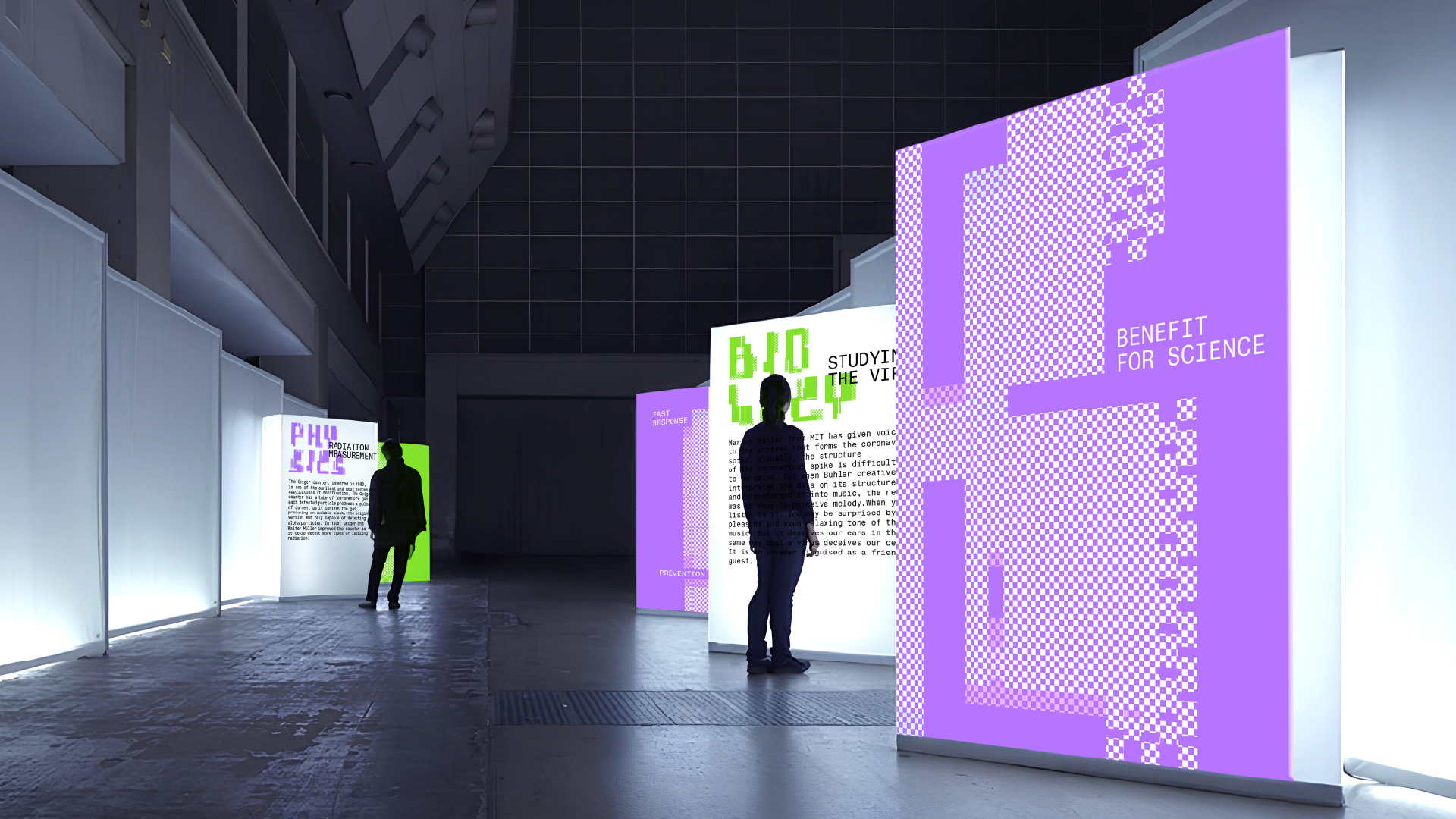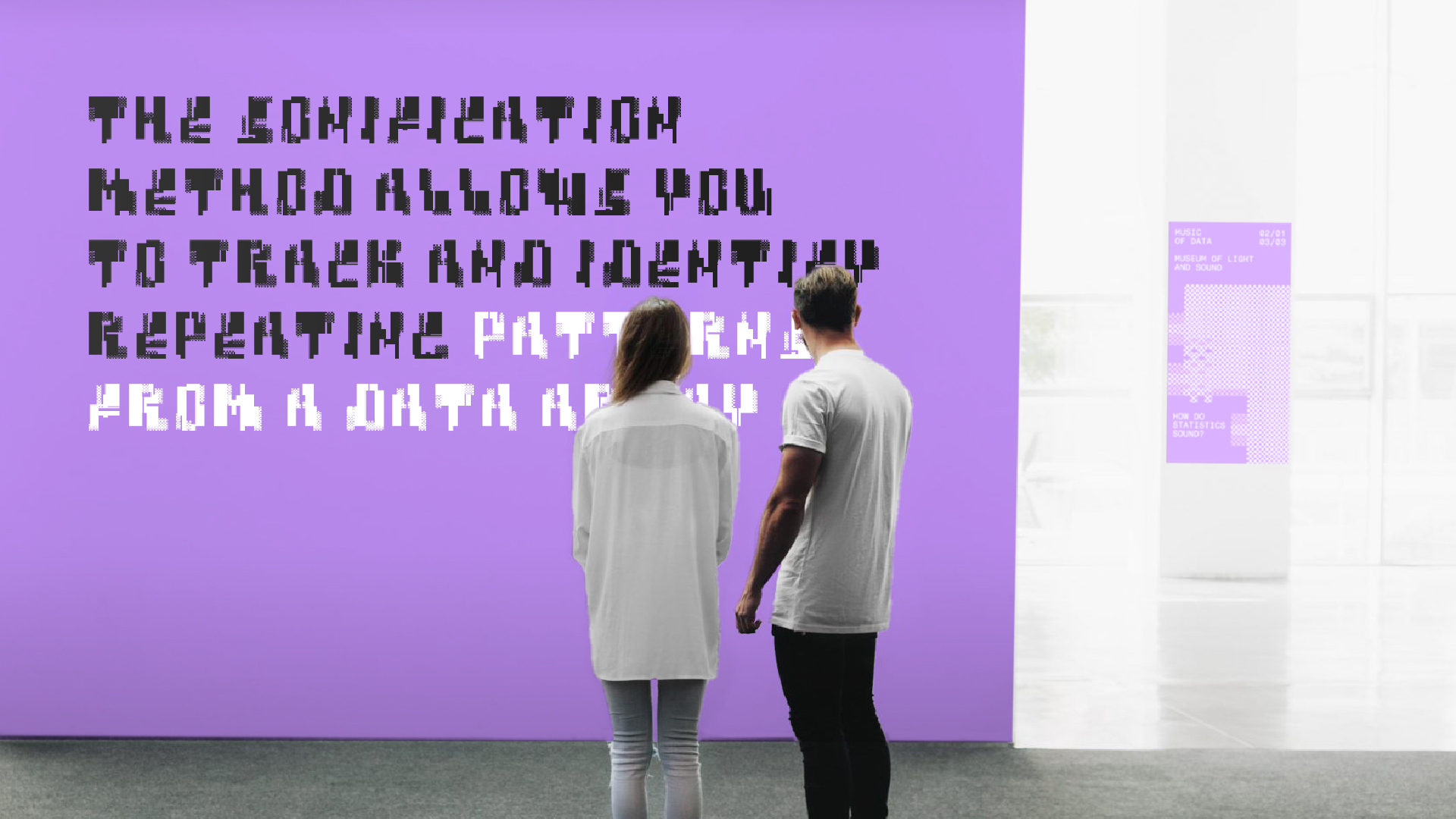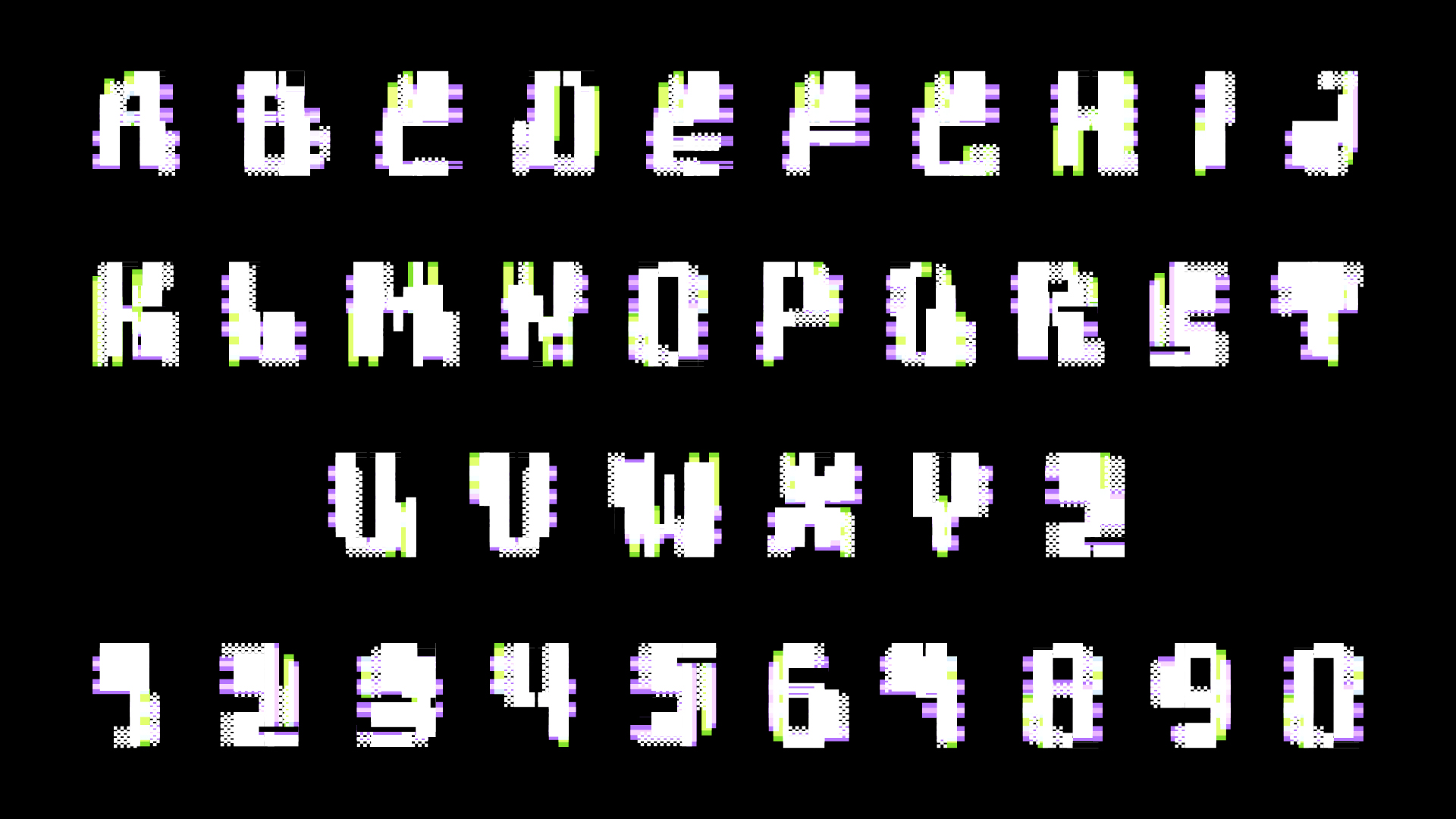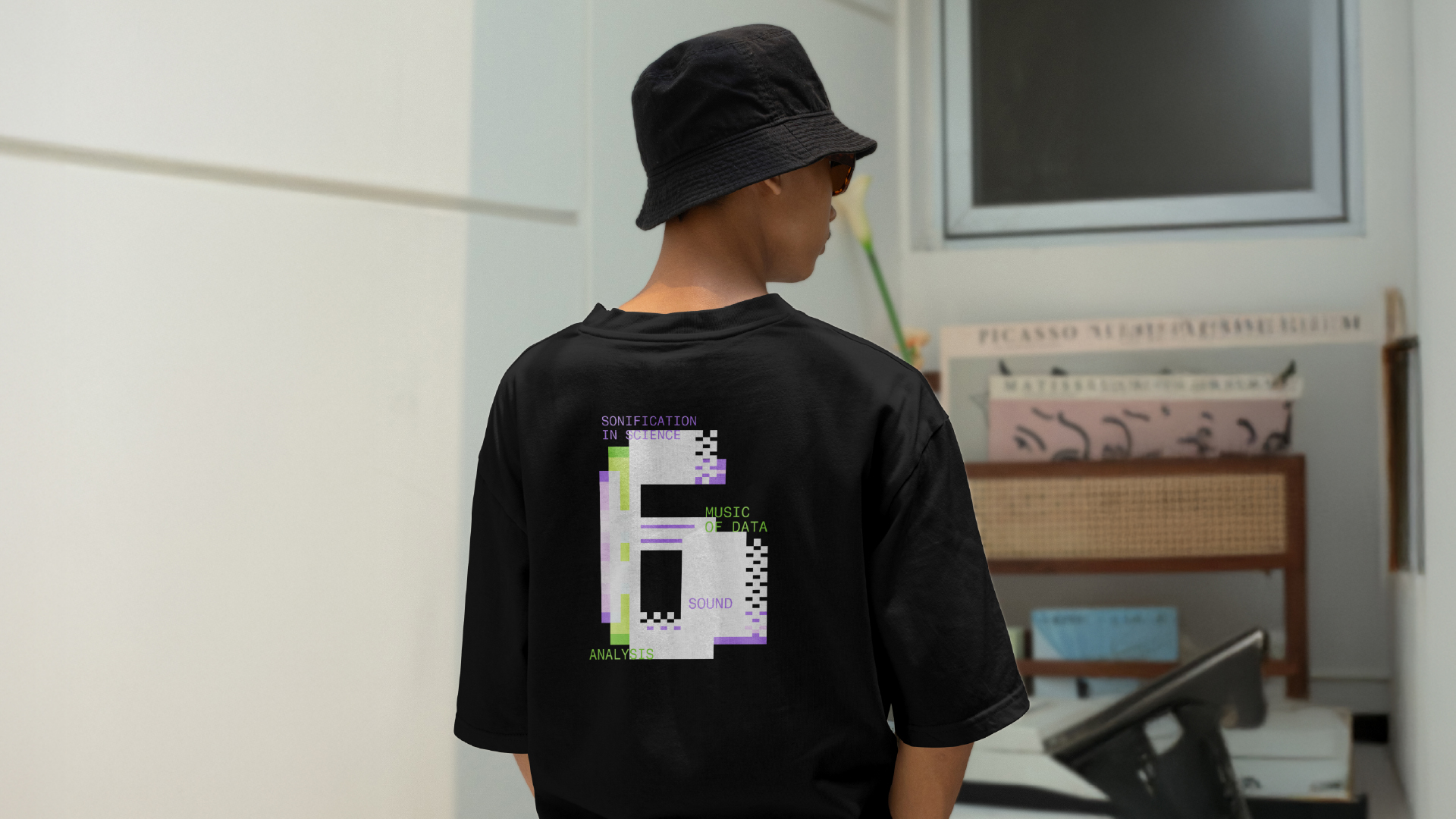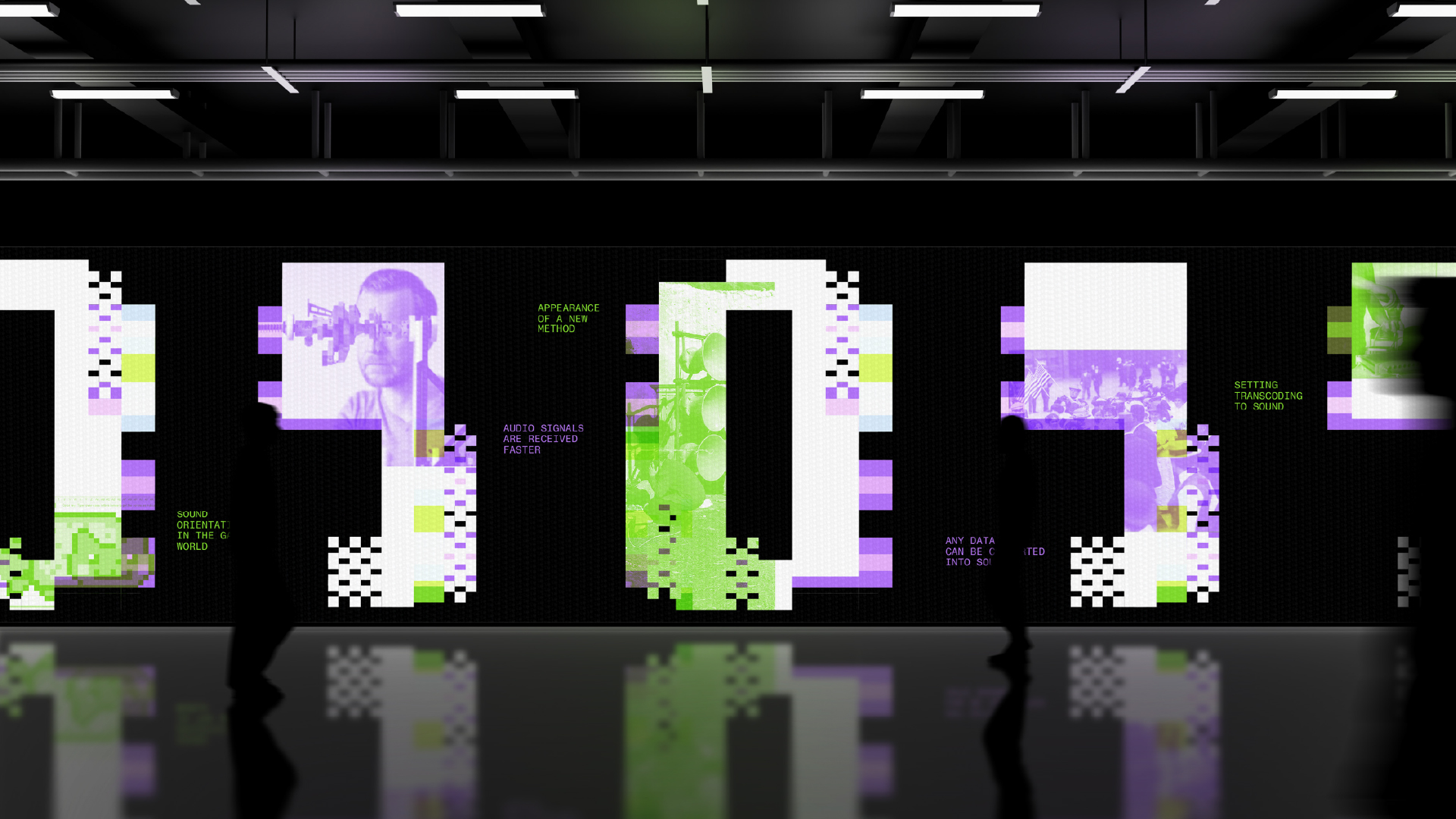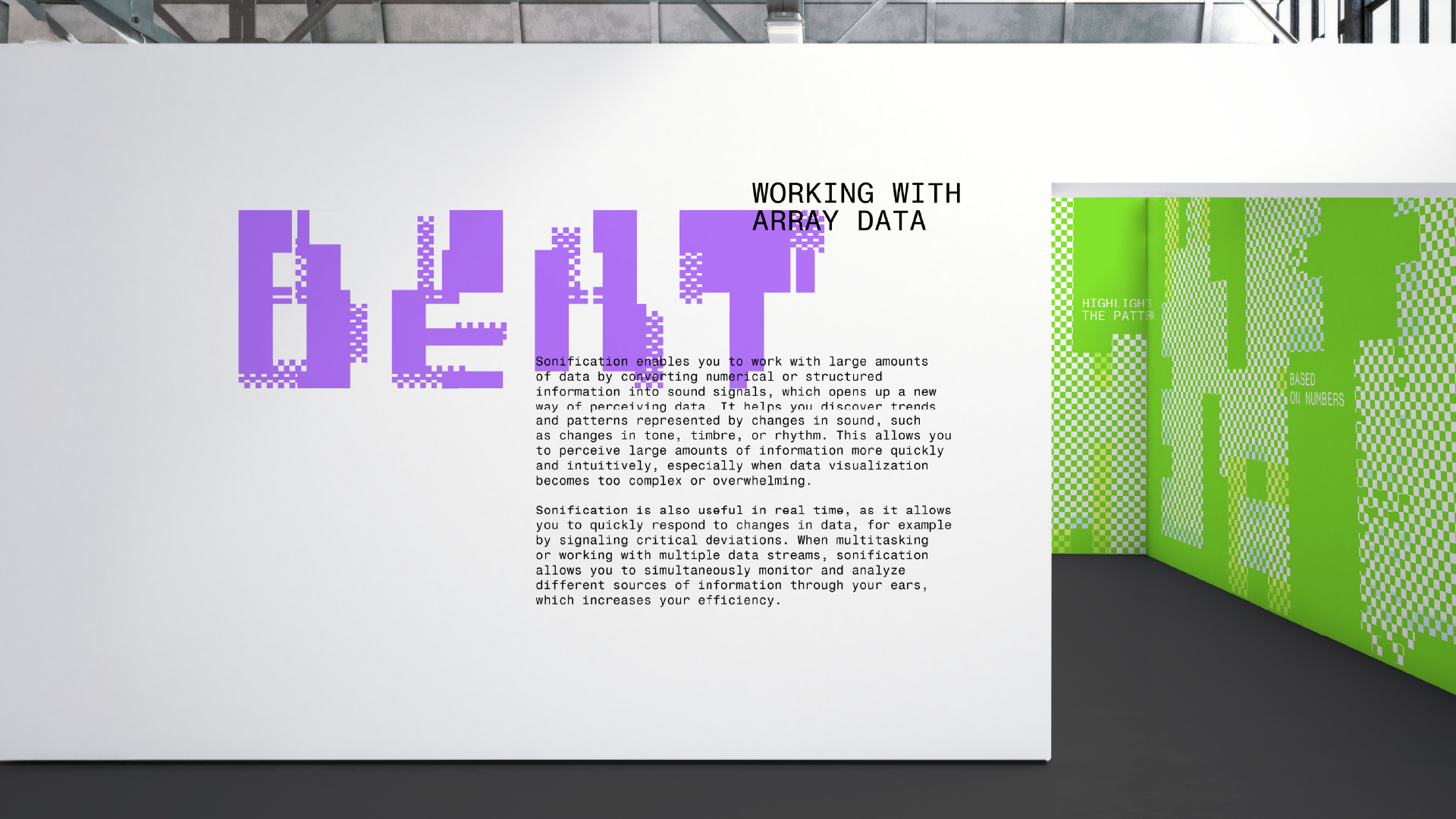
MUSIC OF DATA
Проект шрифта разработан для айдентики аудиовизуальной выставки, посвящённой сонификации — методу представления данных через звук. Сонификация отображает параметры набора данных в свойствах звука. Человеческий слух особенно чувствителен к ритмам, повторениям и микросдвигам высоты и громкости, поэтому этот метод помогает распознавать закономерности в больших массивах информации, расширяя способы аналитического восприятия.
В основе концепции шрифта — работа с массивами данных и выявление в них структур. Каждый знак собран из сочетания простых фигур — квадратов и прямоугольников. Поодиночке эти элементы остаются абстрактными, но при наложении друг на друга рождают узнаваемую букву. Читаемость возникает как результат взаимодействия слоёв — так же, как в сонификации смысл проявляется в паттернах звучания.
У шрифта две итерации. Первая — цветная, первоначальная версия с полным набором слоёв. Знаки в ней работают и в совместном наборе, и поодиночке, выступая отдельными композициями на носителях. Вторая — монохромная, в которой цветные слои удалены. Эта версия держит форму букв и без них, продолжая идею выявления конкретных структур из массива элементов.